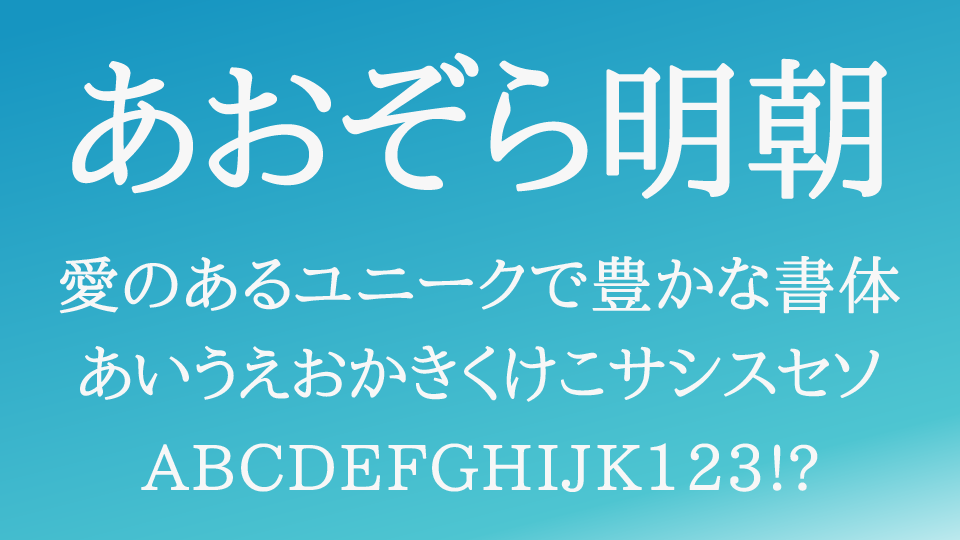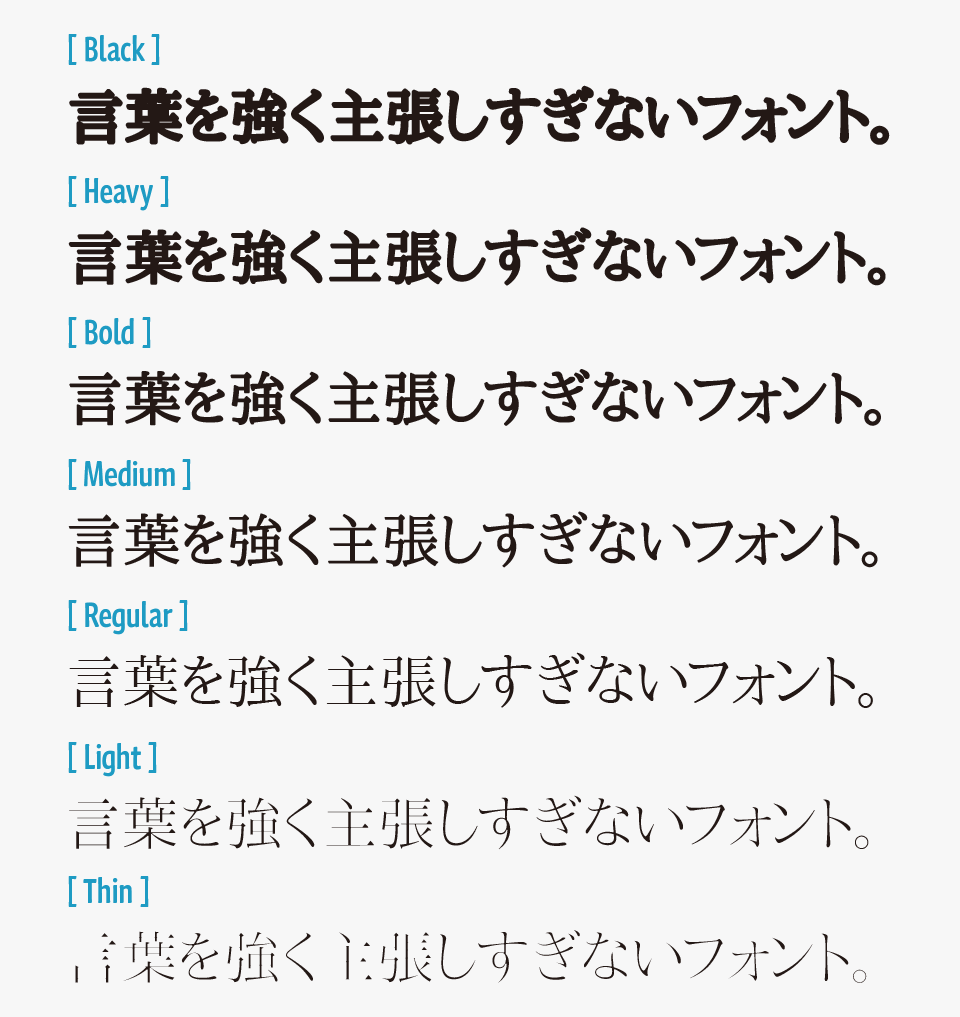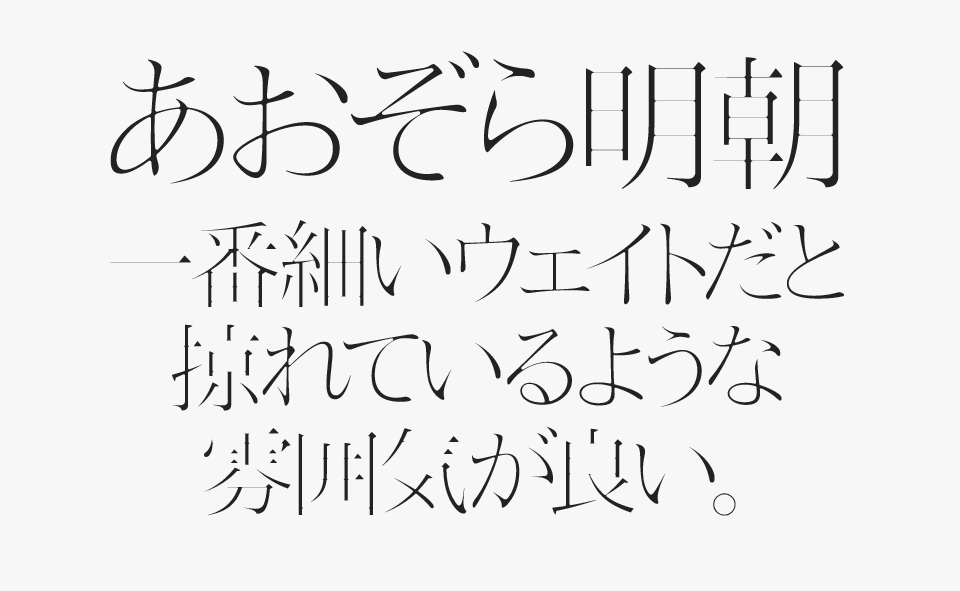
あおぞら明朝フォントは、IPA P明朝をベースに制作された、すっきりと爽やかな印象を持つ明朝体フォントです。
明朝体らしい上品さや読みやすさを残しながら、全体的に軽やかで整ったシルエットになっているため、古典的すぎず、現代的なデザインにも取り入れやすいところが魅力のフォントです。
やわらかさとシャープさのバランスが心地よく、本文からタイトルまで幅広いシーンで活躍してくれるフォントとなっています。
あおぞら明朝
フリーフォントでは意外と少ない“超極太ウェイト”が用意されているところも大きな特徴です。あおぞら明朝には7種類のウェイトが収録されており、新聞の見出しのようなインパクトある極太表現も可能になっています。繊細な文章組みから、力強いタイトルデザインまで幅広く対応できる、実用性の高い明朝体フォントです。
収録されている太いウェイト(Black・Heavy・Boldなど)は使うシーンを気をつけないと、少し潰れた印象になるので、要注意です。
あおぞら明朝の7種類のファミリーを比較
また、一番細いウェイトの「Thin」は、文字がかすれているような独特の質感が魅力で、繊細さの中に味わい深さを感じられる素敵なフォントです。
あおぞら明朝のThinを使った事例
収録文字は、ひらがな・カタカナ・漢字はJIS第4水準・IBM特殊記号・英数字が収録されています。